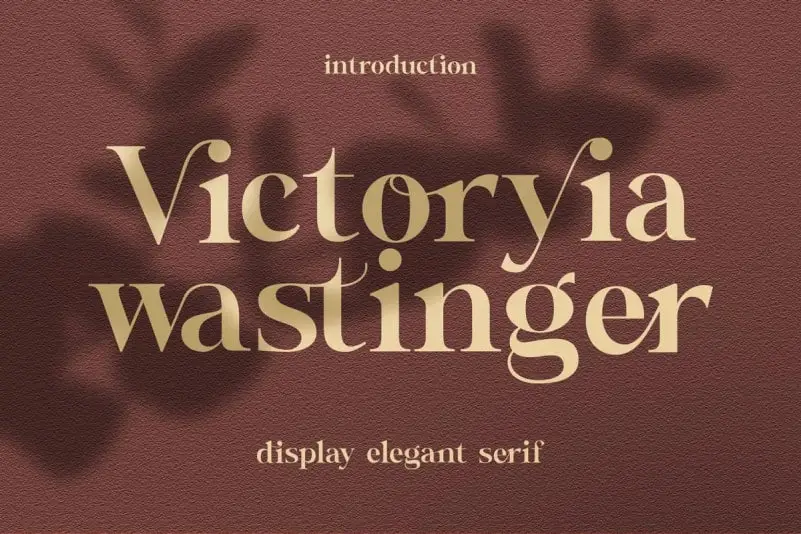
A Wastinger Serif Font é uma tipografia serifada autêntica e aconchegante criada pelo Studio Typetemp com alternativas, ligaturas e suporte multilíngue. É perfeita para projetos editoriais, criação de logotipos, rótulos de marca, embalagens de produto, cabeçalhos de revistas ou simplesmente como um fundo estético sob qualquer imagem de fundo. Esta fonte serifa é uma escolha inteligente para designers gráficos, permitindo criar design visual arredondado e sofisticado sem comprometer a legibilidade. Com seu amplo leque de opções, Wastinger Serif torna-se um recurso inestimável para trabalhos gráficos que valorizam tanto estilo quanto precisão textual.